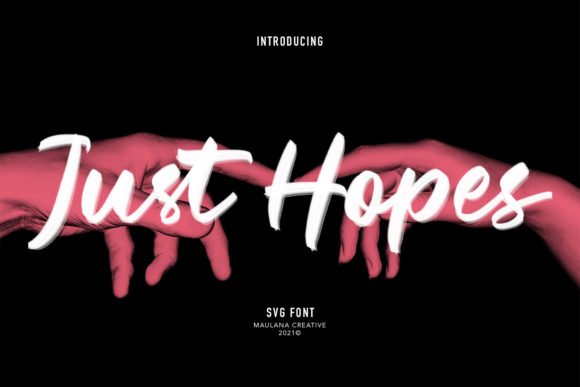
[Creativefabrica] Just Hopes Font (2021)
Just Hopes - это прекрасный и неподвластный времени рукописный шрифт.
Это лучший выбор для создания привлекающих внимание логотипов, брендинга и цитат.
Каждая буква имеет уникальный и красивый оттенок, благодаря которому ваш дизайн оживет!